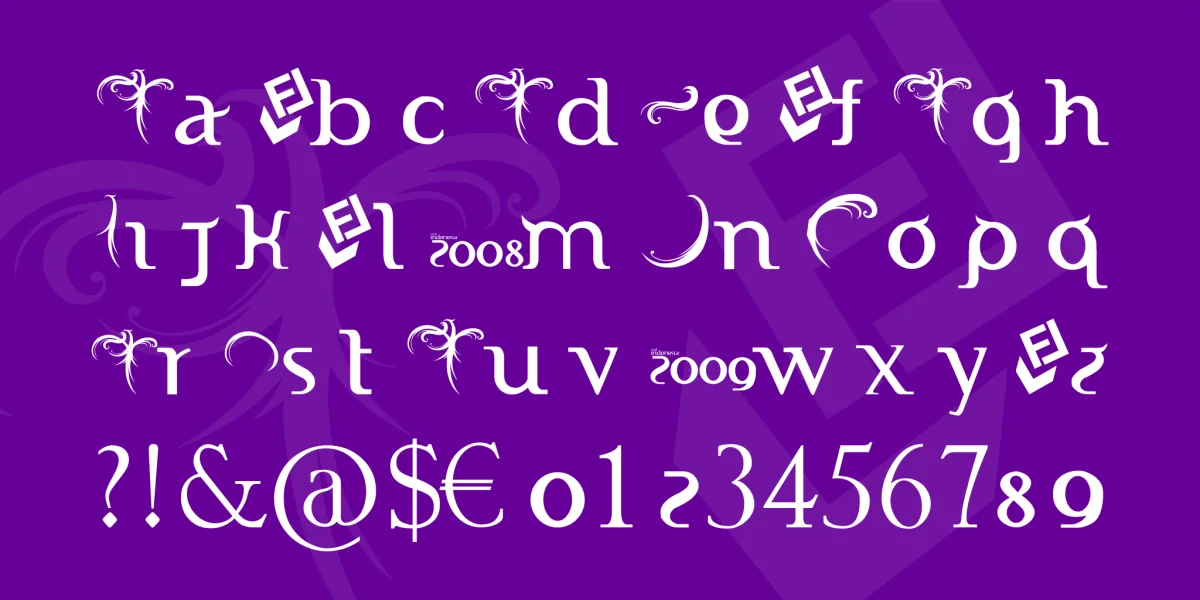
Suatu kebanggaan bagi Fizz-Labz dan FTF merangkai huruf ini menjadi alfabet utuh dari a-z "lowerchase"
dari logo pariwisata Visit Indonesia 2009, font ini bersifat free (free font) yang hanya boleh dipakai untuk pribadi, pendidikan dan bukan untuk kepentingan komersil.